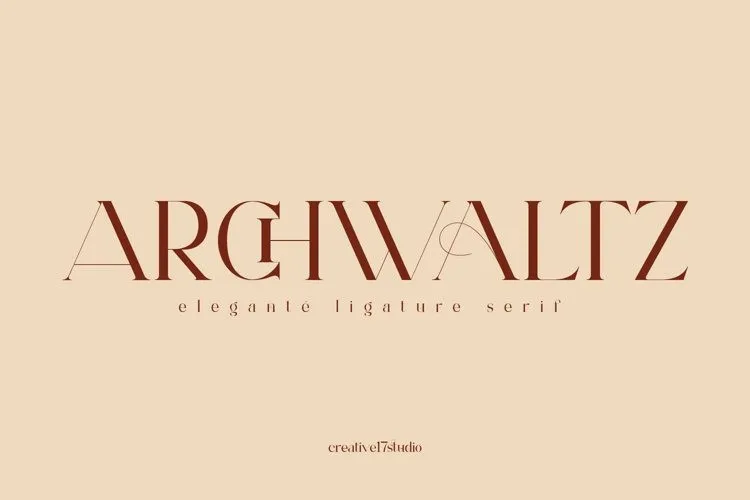
Archwaltz Serif Font – Fonte Grátis
Archwaltz Serif Font
A Archwaltz Serif é uma tipografia serifada original e divertida criada pelo Irfan Hidayat. Ela oferece um impressionante toque luxuoso e moderno, que se destaca pela sua aparência elegante e suave. Com inúmeros ligantes refinados, essa fonte não quererá que você esqueça sua beleza única. Uma excelente escolha para textos de negócios sofisticados ou design gráfico exuberante. Descubra a verdadeira personalidade desta fonte na Irfan Hidayat e transforme suas produções digitais em uma experiência visual memorável.